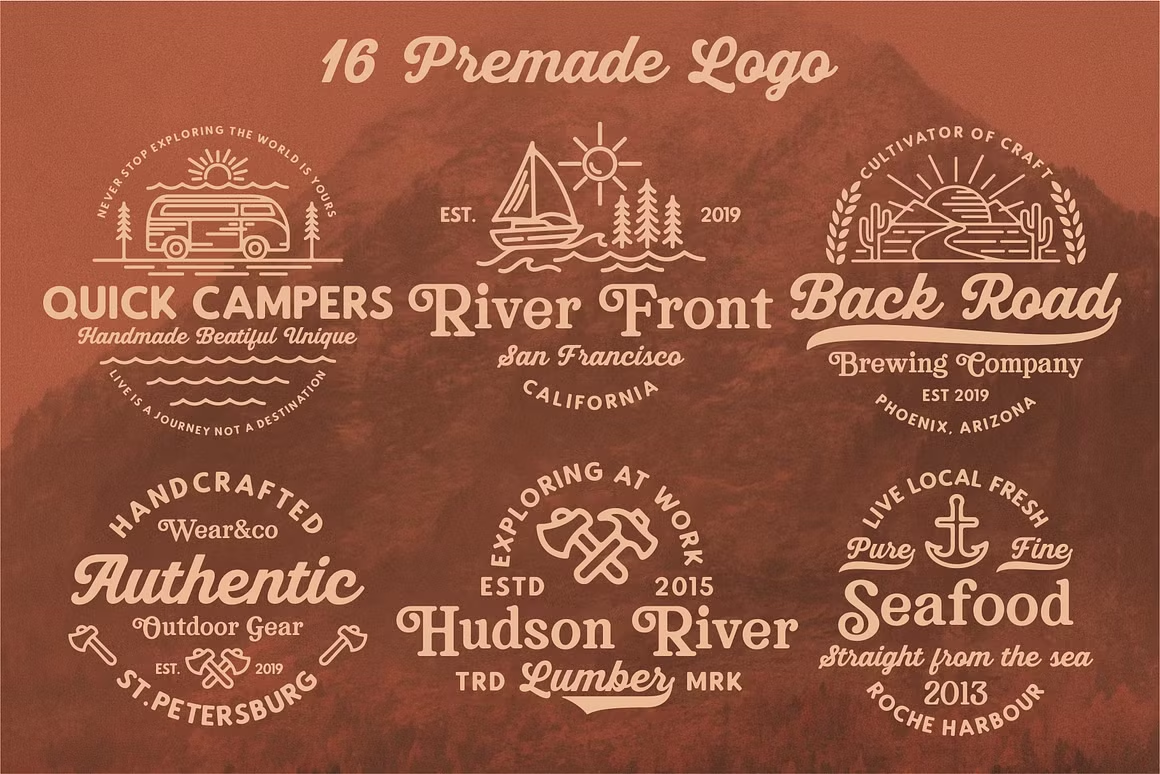
Bookman Font
Description de Bookman Font
Présentation de Bookman Font Collection, une famille de polices tout compris destinée à améliorer vos œuvres typographiques et à leur donner une touche de beauté gracieuse et avancée. Cet ensemble contient huit polices distinctes, chacune d’une race différente (Serif, Sans, Script) avec deux styles (Clean et Press), vous permettant de libérer votre imagination.
Avec une attention portée aux moindres détails et le plus grand soin, la Bookman Font Collection est idéale pour produire des œuvres typographiques impressionnantes qui ne manqueront jamais de surprendre. Ces polices parleront, que vous créiez des t-shirts, des logos, des affiches, des imprimés de magazines ou des designs typographiques accrocheurs.
Mais ce n’est pas tout : la collection de polices Bookman est également livrée avec 16 modèles de logo modifiables pour Adobe Illustrator (CS et CC), vous permettant de les modifier et de les ajuster efficacement à vos besoins spécifiques en matière de marque. À l’intérieur du pack, vous obtiendrez également des dessins flatline dessinés à la main, un formidable détail artisanal pour vos projets les plus originaux.
La collection de polices Bookman est l’une des préférées des designers à la recherche d’excellence, de polyvalence et d’élégance. Que vous soyez un professionnel expérimenté ou un débutant, ces polices vous permettront de réaliser une œuvre d’art typographique captivante et inspirante.